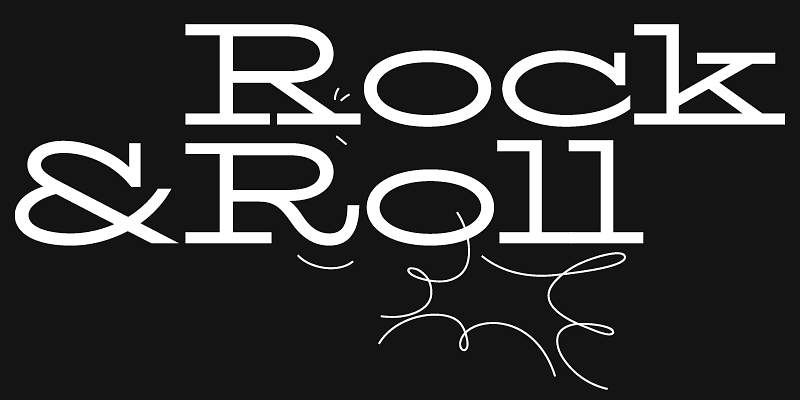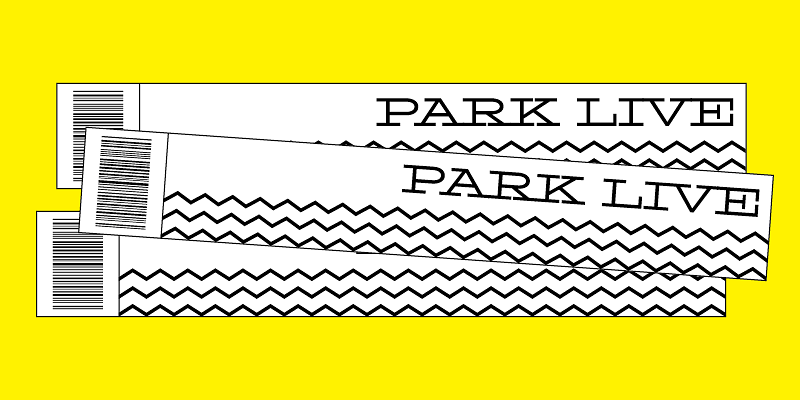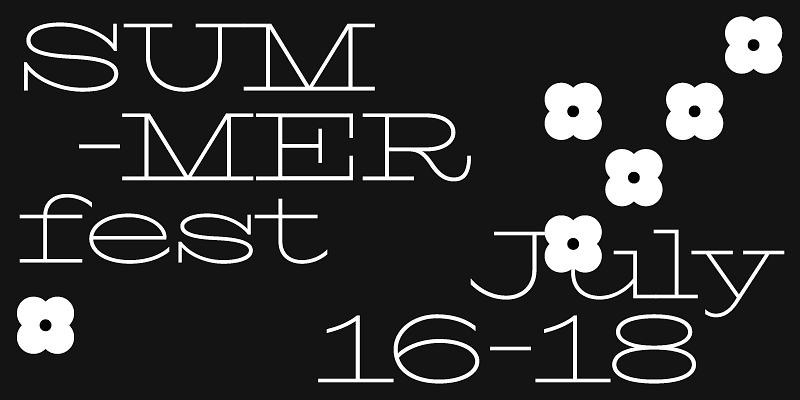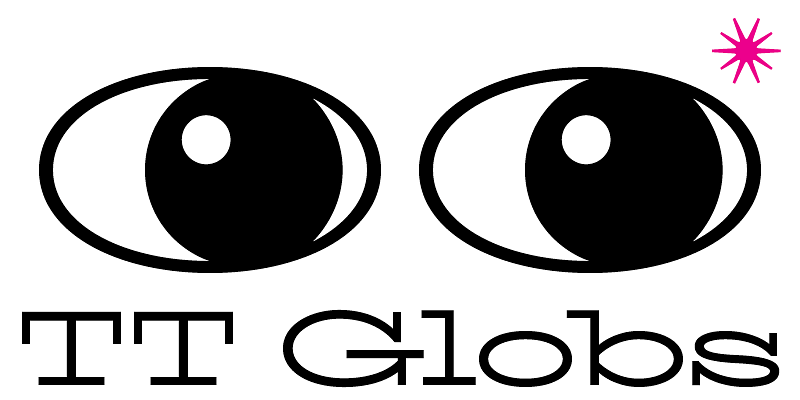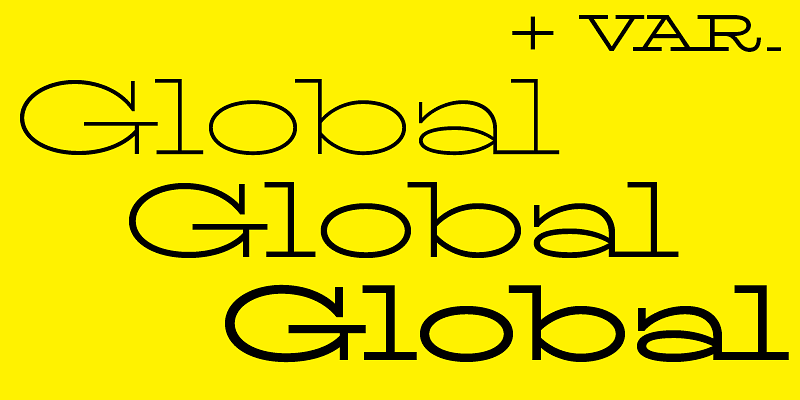
TT Globs는 역사적 슬래브를 글꼴과 그 용도 및 문자 표시 모양에 대한 현대적 인식과 통합하려는 아이디어에서 영감을 받아 개발되었습니다. 곡선을 좀 더 기계적이고 모듈식으로 만들고 싶었으나, 이는 역사적인 표본의 포근한 느낌의 선과는 매우 대조적이었습니다.
TT Globs의 주요 시각적 특징은 긴 디스플레이 세리프입니다. 이 세리프는 통합된 텍스트 이미지를 만들어 내고 모든 문자, 특히 대문자를 끊김이 거의 없는 동적 체인으로 연결합니다.